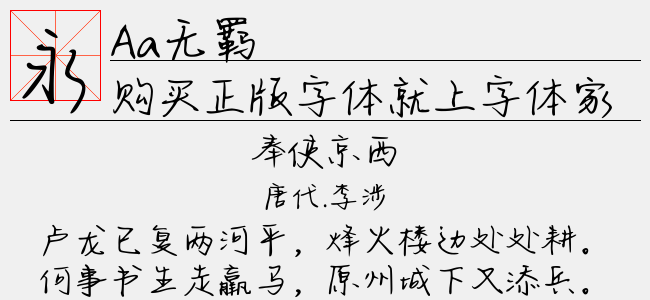
Aa无羁-Aa字体
Aa无羁是一款大小5.20 M的Aa字体字体,主要特征是手写,手书风格,个性,行书,,Aa无羁为TTF格式的文件,采用安装嵌入,包含了符号拉丁文日文中文,字宽中等(正常),当前版本是Version 1.000,共计6763个汉字以及附加其他英文字体和阿拉伯数字。
字体作者:Aa字体
字体名称:Aa无羁